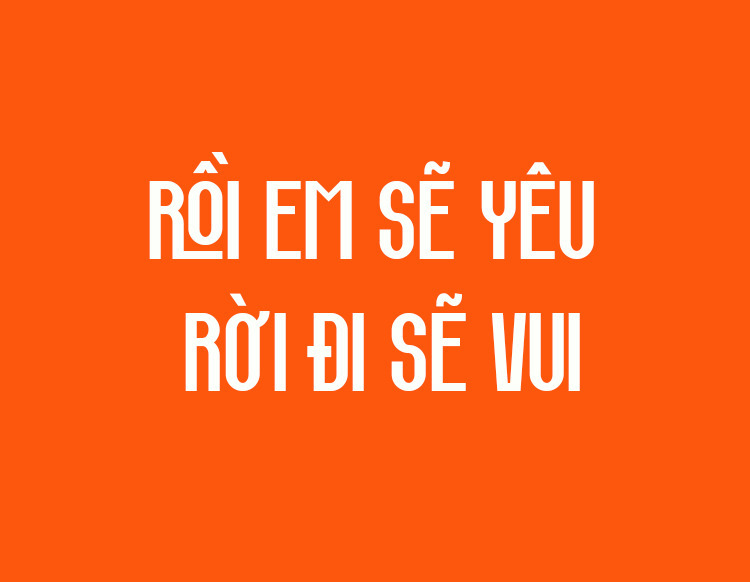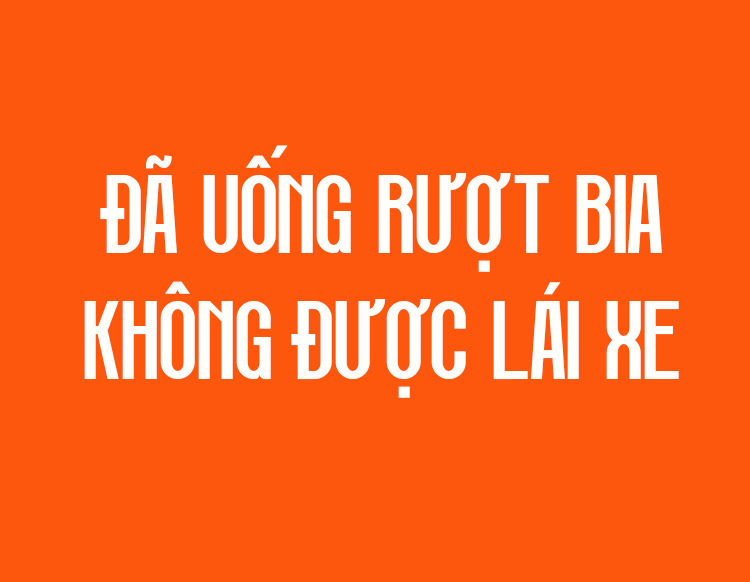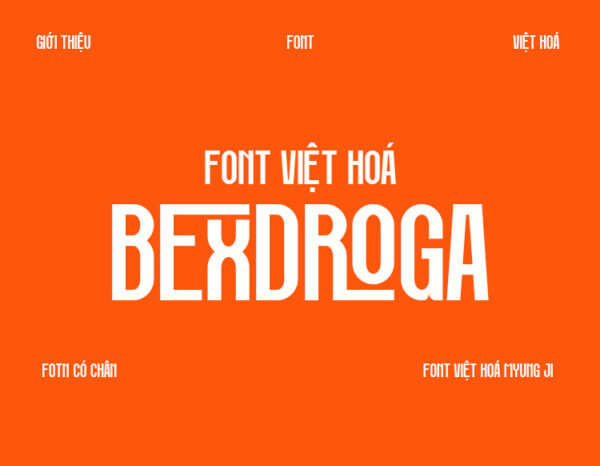
Font việt hoá MJ Bexdroga là một font chữ tinh tế, được thiết kế khéo léo để trở thành một phông chữ được yêu thích khi bạn nhìn thầy nó.
Font Bexdroga này vẫn giữ được đương đại và chắc chắn. Nếu bạn yêu thích font này hãy dùng nó trong các thiết kế của bạn.